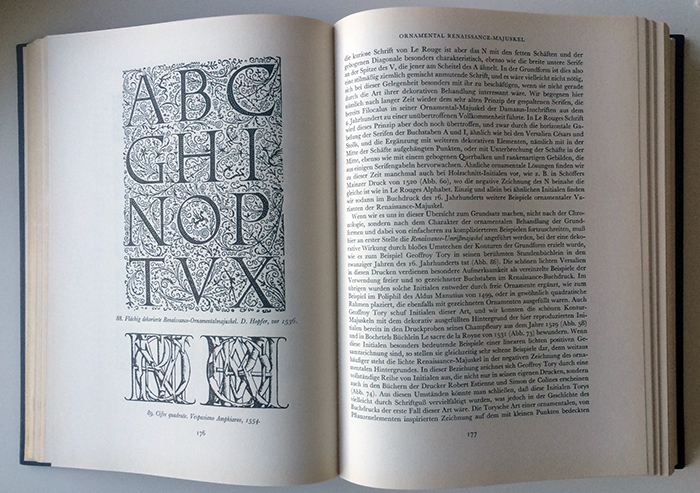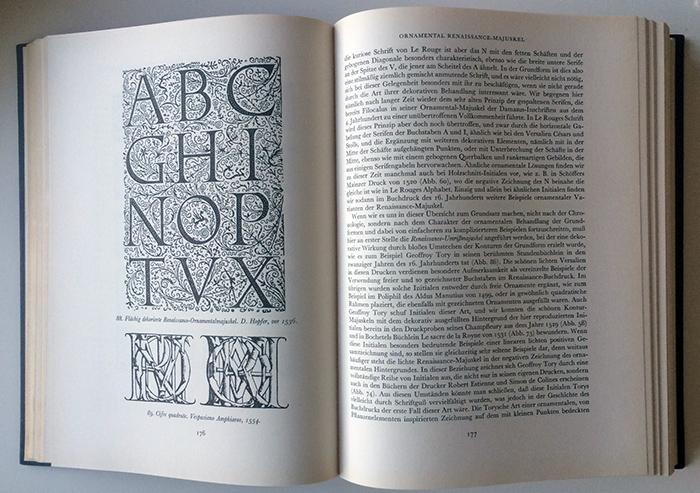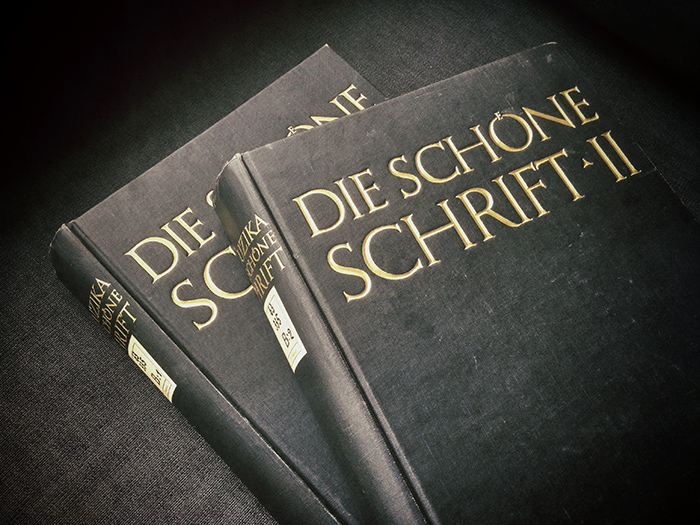
František Muzika (1900–1974) war ein multidisziplinärer tschechischer Künstler. Aus seinem langjährigen Interesse an Schrift entstand das zweibändige Werk Die schöne Schrift (im tschechischen Original: Krásne písmo ve vývoji latinky I, II 1958/1963), eine beispiellose Darstellung der Entwicklung der lateinischen Schrift.
In Wort und Bild werden, von den sumerischen und ägyptischen Anfängen ausgehend, die mannigfaltigen Schriftsysteme, die schließlich zur Entwicklung des lateinischen Alphabets führten, besprochen und abgebildet. Auf die vielen Darstellungen der lateinischen Monumentalschrift folgen Quadrata, Rustika, Unziale und Halbunziale bis zur karolingischen Minuskel. Ein Kapitel ist der römischen Kursiv in ihren mannigfachen Spielarten gewidmet. Im zweiten Teil des ersten Bandes kommen die gebrochenen Schriften in drei ausführlichen Kapiteln zur Darstellung.
Der zweite Band ist ausschließlich der Antiqua vorbehalten und bespricht die Schriftentwicklung von der Renaissance bis in die Mitte des 20. Jahrhunderts. Allein vier Kapitel befassen sich mit den Schriften aus der Zeit der Renaissance. Eingehend werden die Antiqua-Buchstabenkonstruktionen der Schreibmeister und Künstler (wie Dürer) behandelt. Danach folgen je ein Kapitel über die Entwicklung der Handschriften, der Druckschriften und der ornamentierten Schriften dieser Epoche. Fünf Kapitel sind anschließend den barocken und klassizistischen Schriften eingeräumt. Der fünfte Teil dieses großangelegten Werkes ist der Entwicklung im 19. und 20. Jahrhundert gewidmet.
Die Anlage der beiden Bände zeugt von tiefem Verständnis für die geschichtlichen und (dies macht das Buch so einzigartig) die gestalterischen Zusammenhänge. Max Caflisch sagte 1960, das Werk »zählt zum Besten, was wir an grundlegenden Werken über die abendländische Schriftkunst besitzen«. Auch 50 Jahre später hat sich daran nichts geändert.
Autor(en): František Muzika
veröffentlicht: 1965
Verlag: Verlag Werner Dausien, Hanau/Main